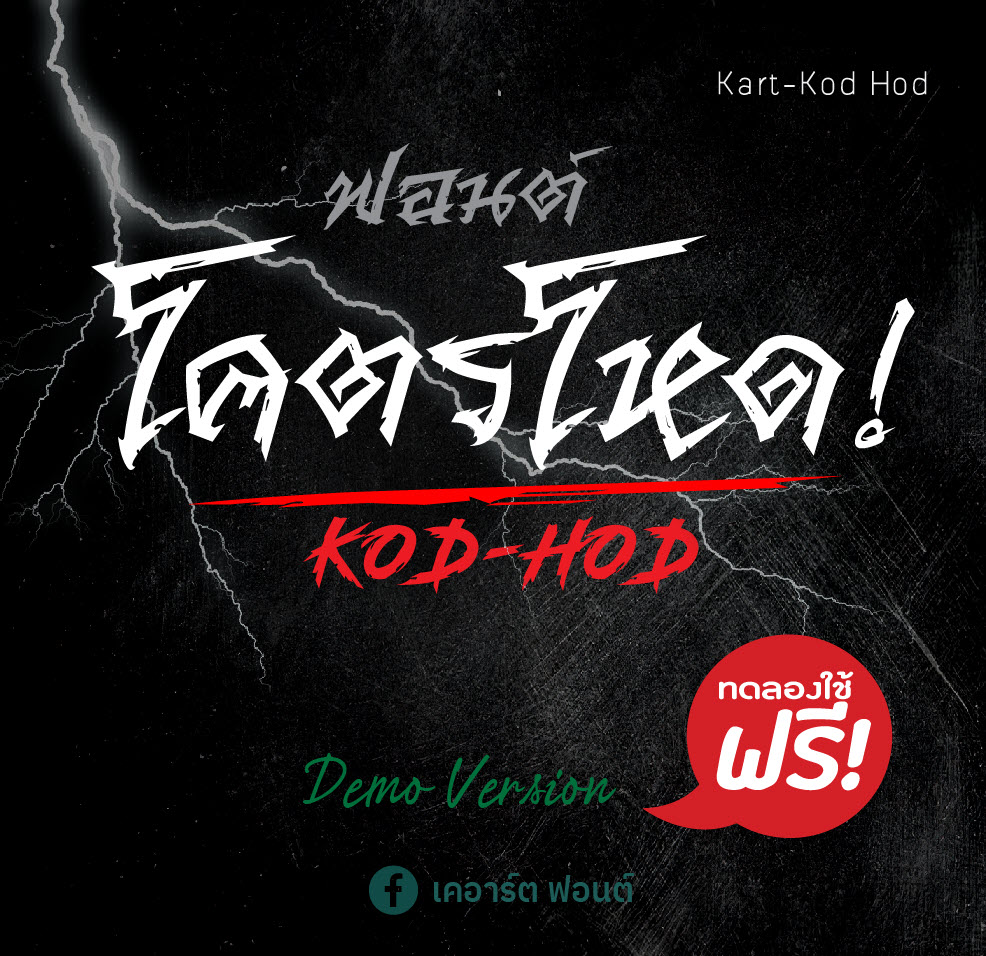
ฟอนต์ เคอาร์ต-โคตรโหด (Kart-Kod Hod )
ฟอนต์ เคอาร์ต-โคตรโหด (Kart-Kod Hod ) เป็นฟอนต์ที่เขียนเน้นดุดันดูน่ากลัวดูอันตราย #ฟอนต์หนังผี #ฟอนต์น่ากลัวเป็นเดโม่ครับ สามารถใช้ครอบคลุมหลายโปรแกรมโหลดทดลอง กับไอแพด และแอนดรอยด์ดูก่อนได้ สนับสนุนผลงงานแบบเต็มพร้อมใบรับรองสิทธิ์ใช้งานเชิงพาณิชย์ตลอดชีพ สนับสนุนได้ 300 บาทครับ